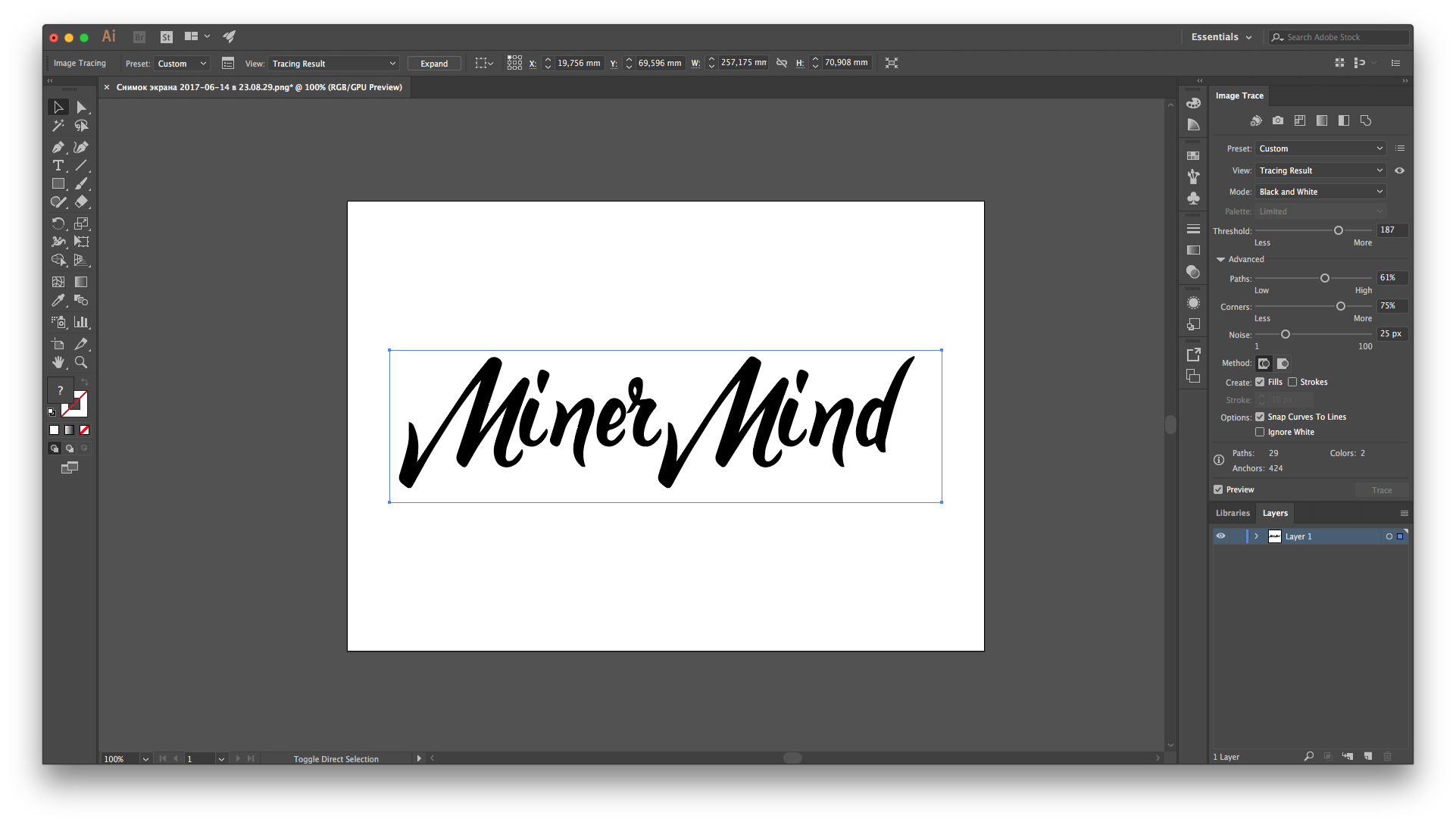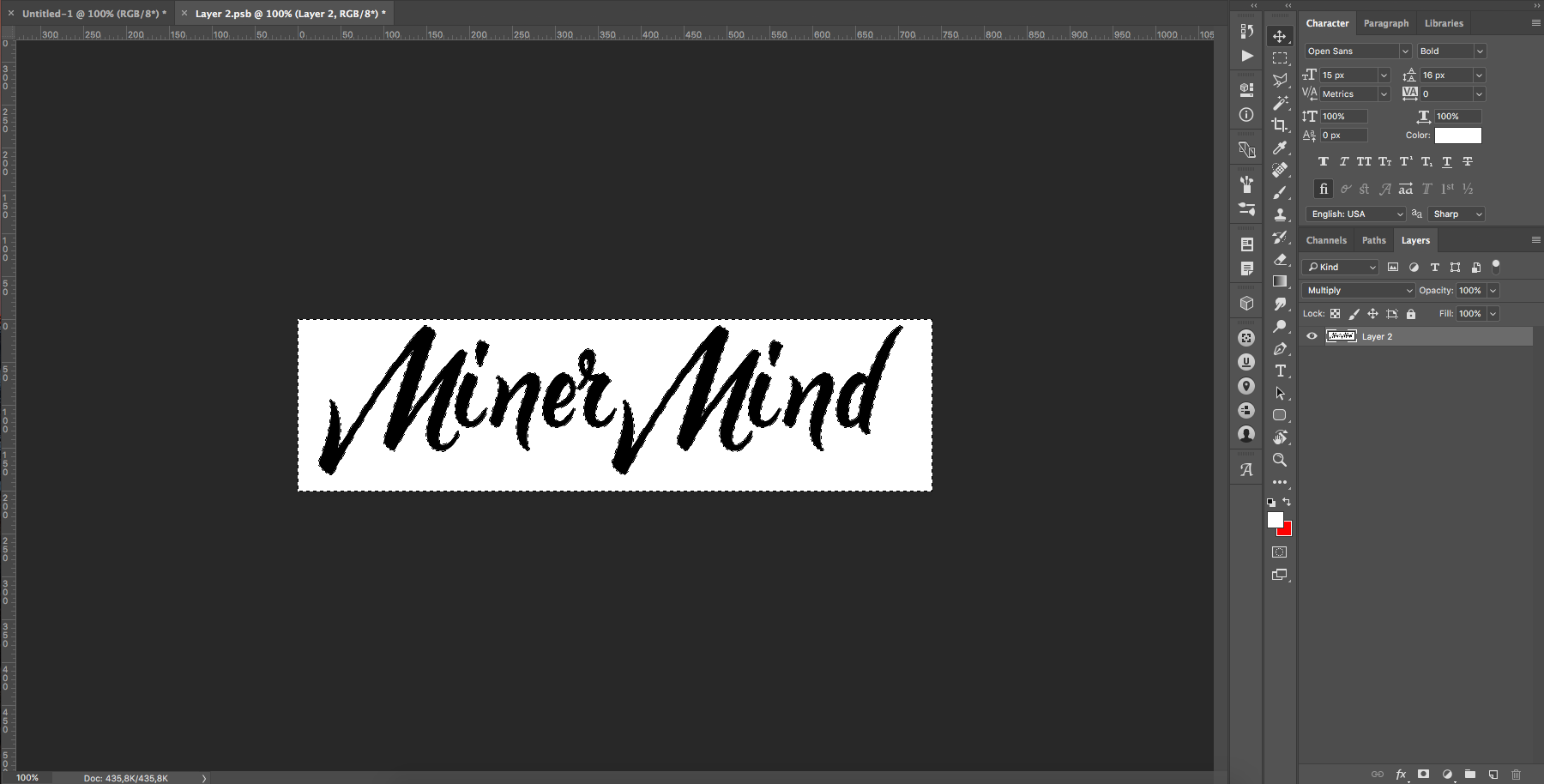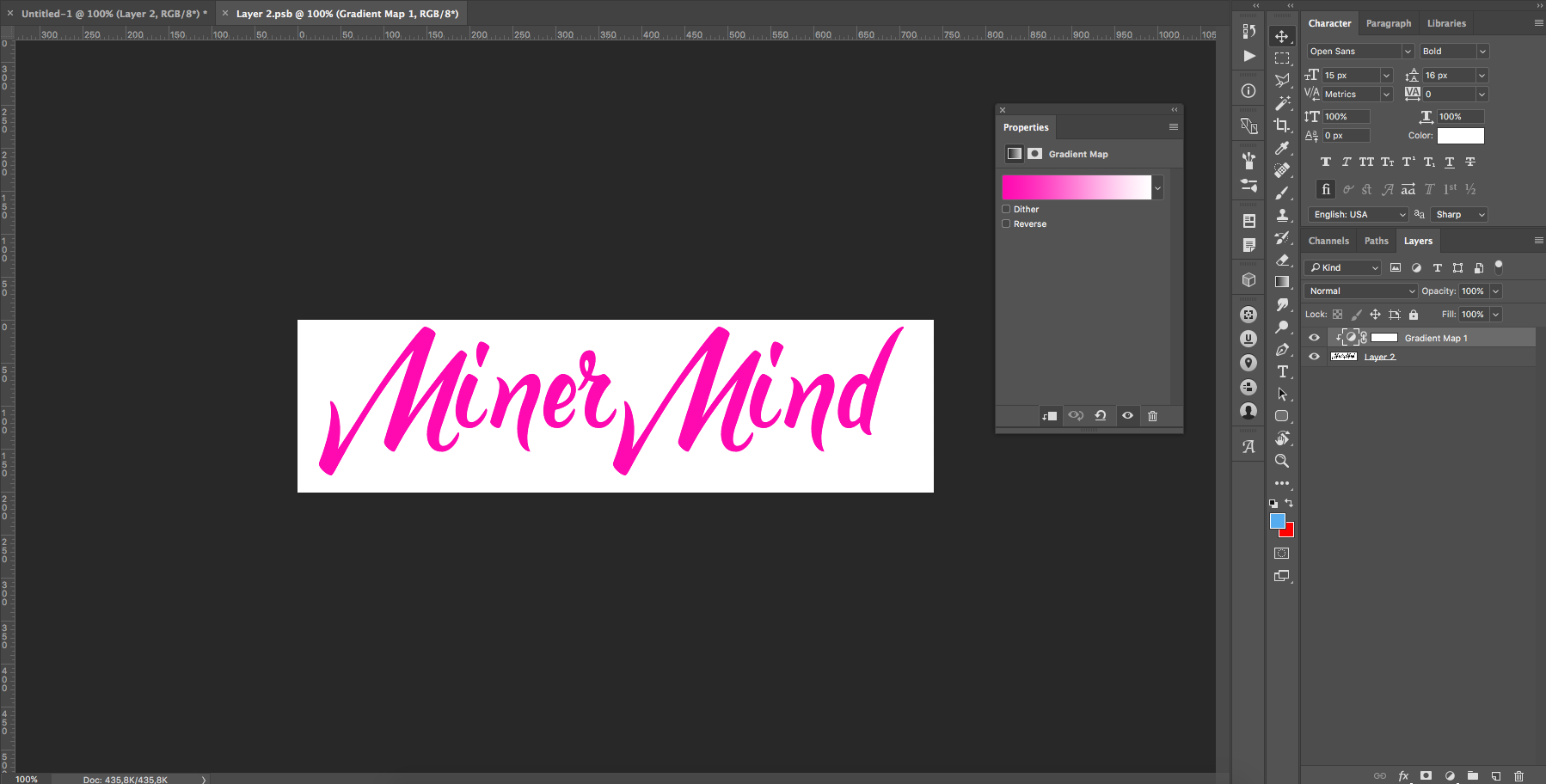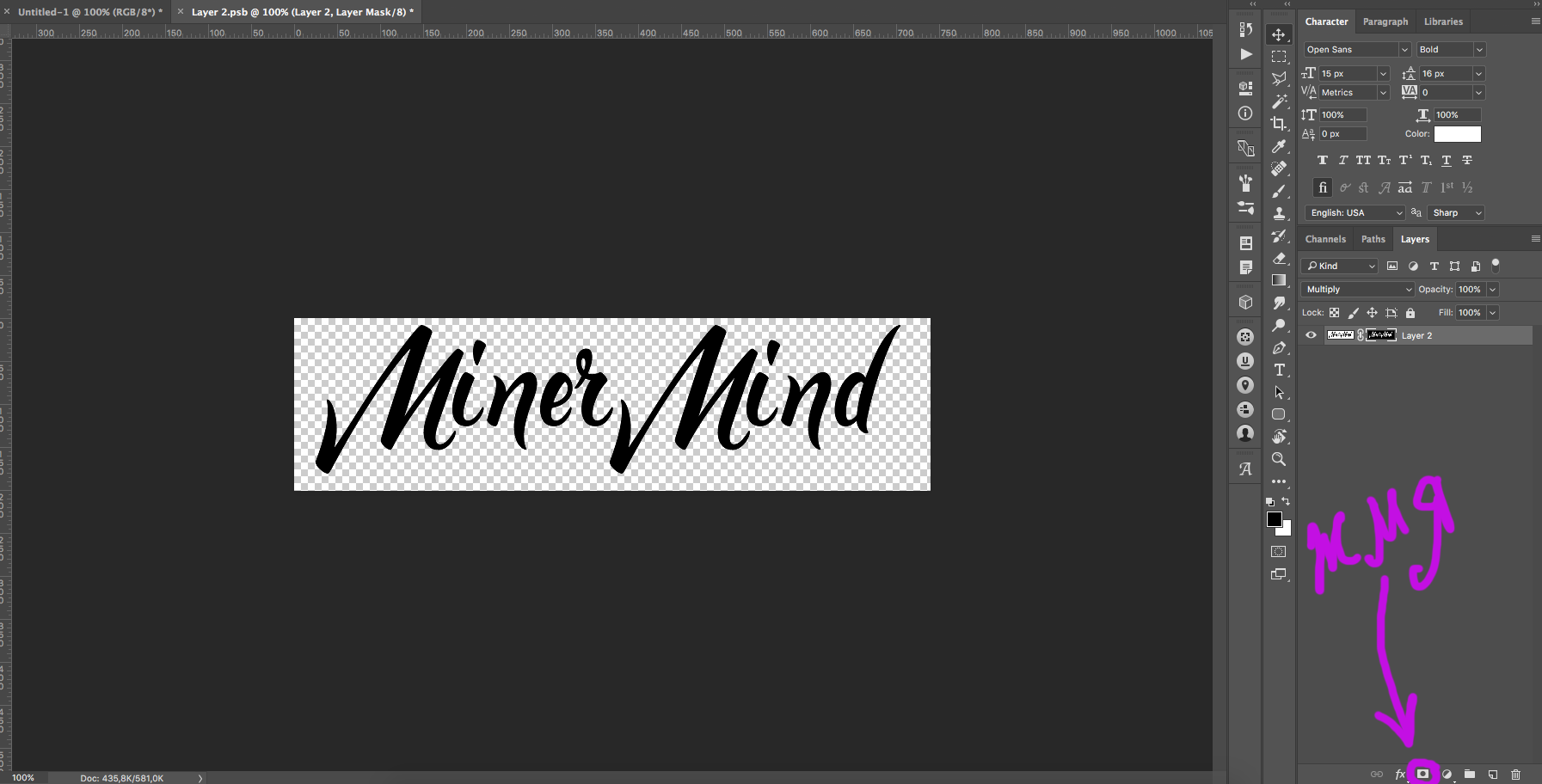
Как найти шрифт по картинке?
Быстрые и медленные способы
Сейчас я вас научу плохому.
Допустим, есть картинка
и нужно найти шрифт, которым сделана надпись, или подобрать похожий по стилю и характеру.
Поиск по картинкам
Идем в поисковые системы и пробуем найти источник изображения, используя поиск по картинке.
Исходную картинку загружаем через форму или кидаем на страницу поиска перестаскиванием.
Порой Яндекс отрабатывает лучше Гугла.
Польза от поисковых систем следующая.
Если мы найдем источник, например, логотипа, то сможем найти автора и, возможно, его портфолио, а в нем — указание на использованные шрифты. Или просто на странице где-нибудь рядом с изображением будет написано название шрифта.
Кто знает, это дело такое. Шансы малы, но не настолько, чтобы их игнорировать. Тем более в безвыходной ситуации.
«Что за шрифт» на MyFonts.som
Идем на Майфонтс в раздел, где работает специально обученный робот.
Мы роботу картинку, он нам —шрифты. Ну или ничего.
Но не спешите отправить ему картинку без проверки и доработки. Учтите, что:
- Робот не понимает кириллицу. Перед загрузкой удалите с картинки все символы, которых нет в латинице. Кириллические символы, совпадающие с латинскими можно оставить.
- У робота плохое зрение. Иногда он путает буквы с нестандартными формами. Поэтому иногда лучше кормить его по одной букве. Стоит найти самую характерную и начать с нее.
После загрузки скорректируйте распознанные символы, введя в ячейки под картинками правильные символы.
Если буква или знак (например, восклицательный) развалилась на две ячейки, перетащите одну картинку на другую и соберите букву назад.
Жмем Continue.
Робот постарается найти оригинал шрифта и предложит подходящие теги для дальнейшего самостоятельного поиска.
Поиск по ключевым словам на MyFonts.som
В поле поиска вбиваем по-английски слово или словосочетание, которое определяет инструмент рисования, характер шрифта или его классификацию.
Наше изображение выполнено как бы фломастером (brush pen). Еще тут подойдут слова типа «каллиграфия» (calligraphic), «от руки» (handwritten) и т.д. Здесь можно воспользоваться тегами, которые предложил робот.
Можно искать термины по-отдельности или объединять их и комбинировать в одном запросе.
Если обязательно нужна поддержка русского или другого языка, то указываем соответствующие настройки в полях расширенного поиска, отсекая мусор в результатах.
Жмем кнопку Search и просматриваем результаты, попутно отмечая для себя подходящие варианты на замену.
На Майфонтсе много вариантов на замену исходному шрифту.
Находим нужный вариант и увеличиваем область просмотра примера до максимума. В отдельных случая можно еще сделать зум в браузере.
Скриним.
Растр
В Фотошопе скрин превращаем в смарт-объект. В смарт-объекте накладываем на него Gradient Map от нужного цвета к белому.
В макете выставляем смарт-объекту режим наложения слоев, например, Multiply.
Для большинства случаев с белым фоном этого достаточно.
Кому этого мало, можете удалить из скрина белый цвет. Color Range…, тыкаете пипеткой в белый фон
получаете выделение по цвету, инвертируете выделение,
сглаживаете его пару раз на пиксель-другой, чтобы граница контура не была такой рваной,
и скрываете все белое под маску
В основном документе уже делаете со смарт-объектом все, что душе угодно, почти как с векторным шейпом.
При уменьшении смарт-объекта неровности контура станут менее заметны. Поэтому лучше скринить с запасом, а потом уже уменьшать до нужного размера.
Вектор
Если нужен вектор, то делаем трассировку в Иллюстраторе.
Открываем скрин из PNG-файла:
На панели Image Trace ставим Mode: Black and White, галочку Preview и аккуратно крутим Threshold и настройки в Advanced:
Получив приемлемый результат, делаем надписи Expand
и получаем вектор на все случаи жизни:
Бесплатные шрифты
Возможно, что искомый шрифт — это не коммерческая история и делался по фану или не для продажи. Тогда нет смысла искать его в официальных магазинах.
Жмем на меню группы и выбираем «Поиск».
На странице поиска пользуем ключевыми словами на русском и английском и меню поиска справа:
Здесь нет хорошего описания и тегирования для шрифтов, но что-то все же можно найти. Плюс можно просто полистать стенку группы в поисках чего-то подходящего.
Медленный способ
Написать на форуме Майфонтса или залить картинку с вопросом в специальный альбом «Бесплатных шрифтов» с просьбой подсказать шрифт.
И ждать ответа как соловей лета.